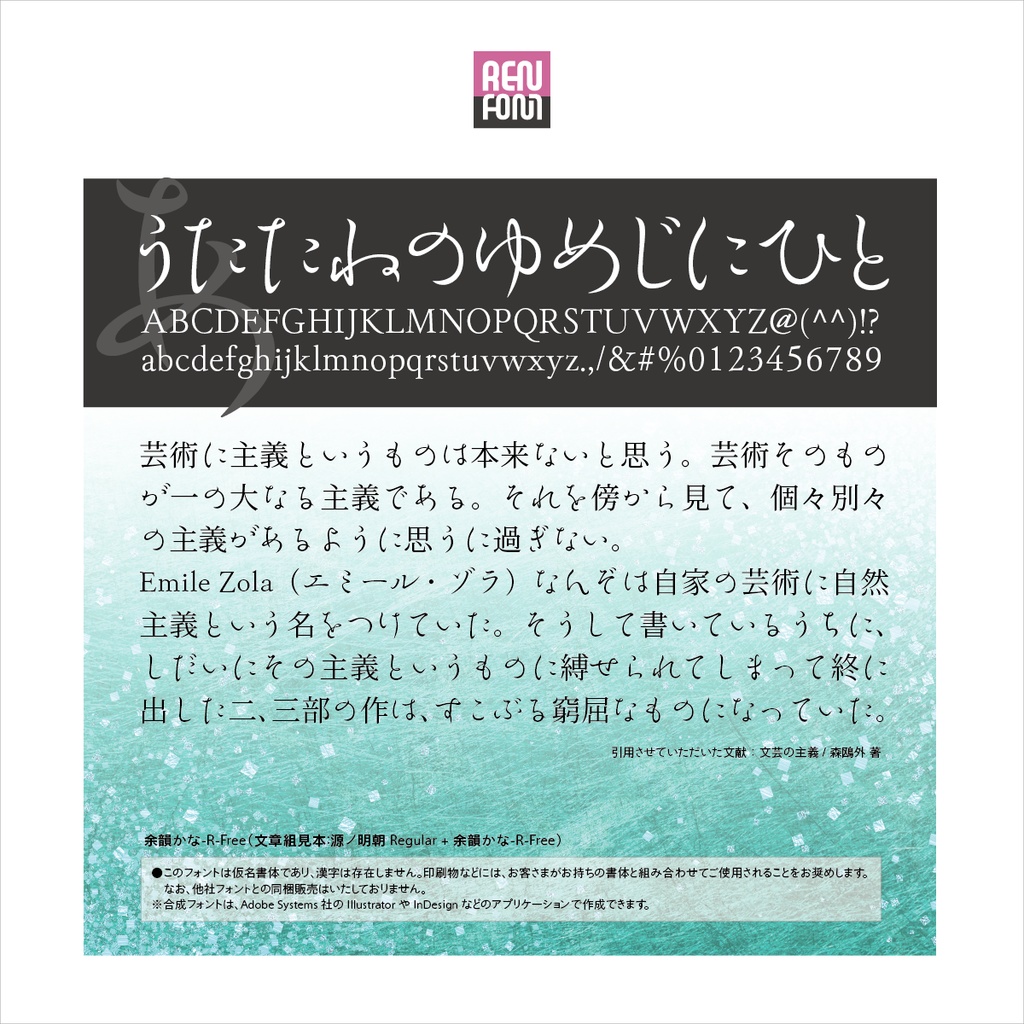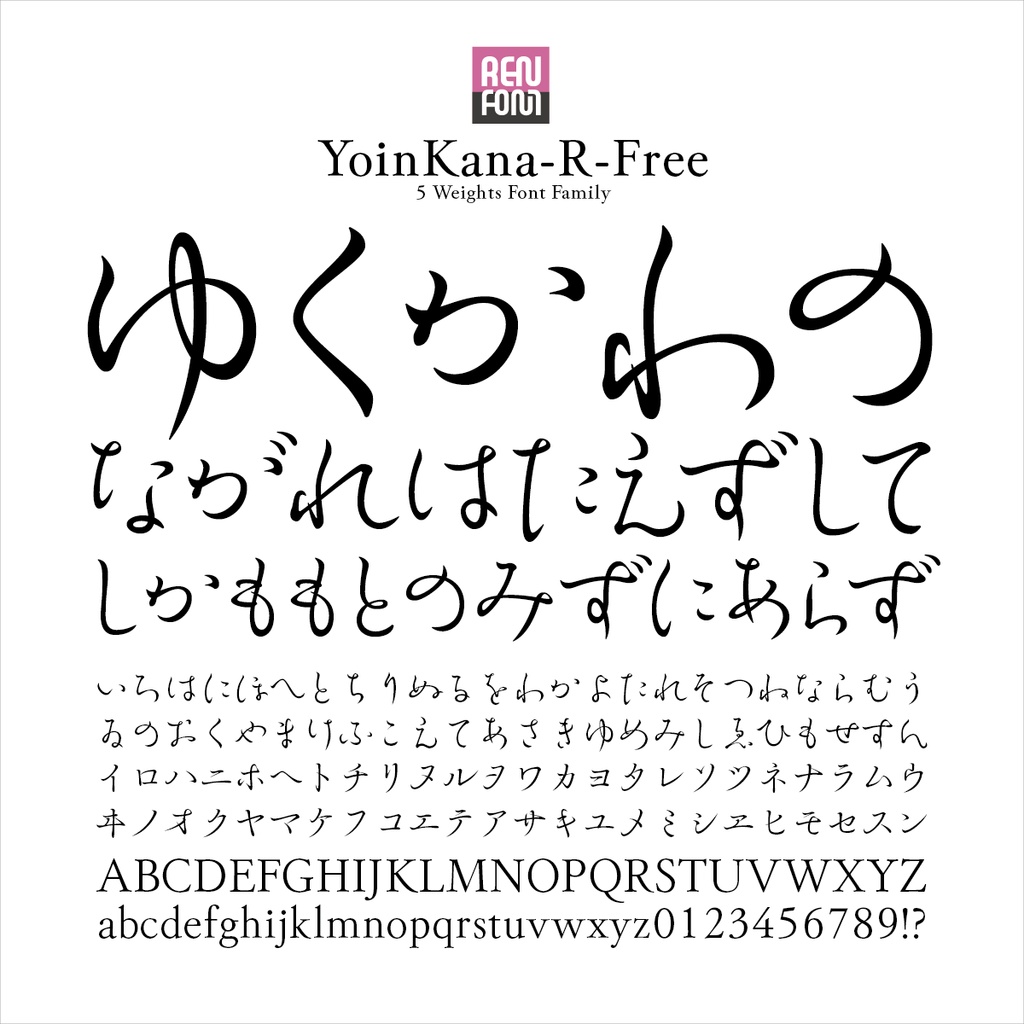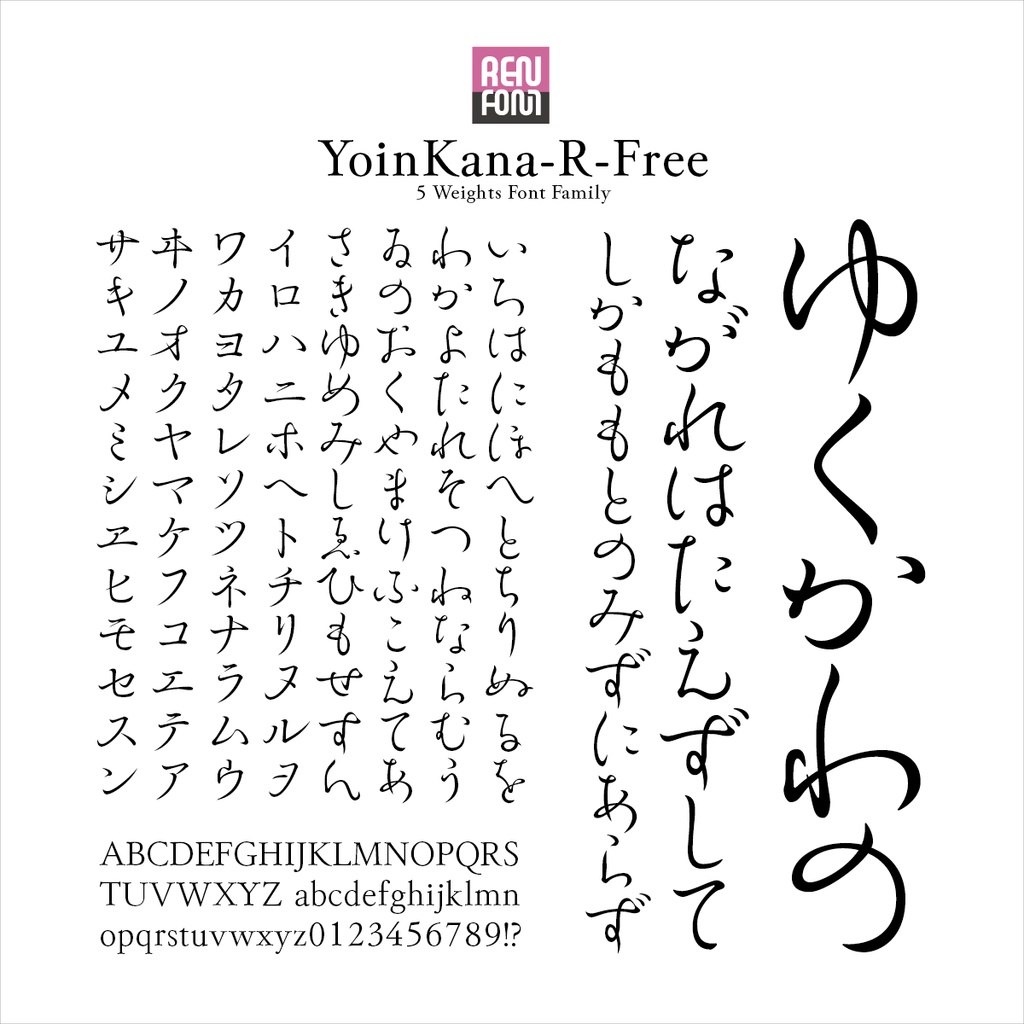
余韻かな-R-Free
味わい深い余韻を残す 余韻かな 5ウェイトファミリー / OpenType
味わい深い余韻を残す印象的な書体。
究極の流麗さを追求した、明朝風と行書風のハイブリッドフォルムフォントです。連綿にすることで、あでやかさは一層強調されますが、多用すると煩さの原因になります。「余韻」は距離の遠い部分、密集してしまう部分は、あえて繋がない選択肢を取りました。一文字ひともじ丹念に心を込めて曲線を描きあげています。その名のごとく心地よい余韻を残してくれる味わい深い書体です。 この書体は、当社タイプデザイナー金井和夫の普段使いの文字をベースとした、明朝・行書の複雑なフォルムイメージを持っています。「L(ライト)」、「R(レギュラー)」、「M(ミディアム)」、「DB(デミボールド)」、「B(ボールド)」の、合計5ウェイトで構成されています。 また、オールドなイメージを残しつつも、その概念にとらわれず大仮名に設計してあるので、近代的な組版にも対応するマルチな性格を備えています。
舞踊・舞踏の心や動きを表現する
余韻かなファミリーの各書体は、まるで日本舞踊のような優雅さ、ワルツのような軽快さを表現しています。ほとんどの文字が正統派の明朝体からはかけ離れたフォルムをしていながら、訴求力や優美さを損なわないよう、細心の注意を払いました。 特徴が強いので、長文には向きませんが、短い本文組みや、ちょっとした見出しに使ってみてください。躍動感に満ちた、訴求力のある紙面になるはずです。縦組み、横組みともプロポーショナル加工を加えました。また、ペアカーニングも緻密にほどこしてあります。
余韻かな-R-Freeについて